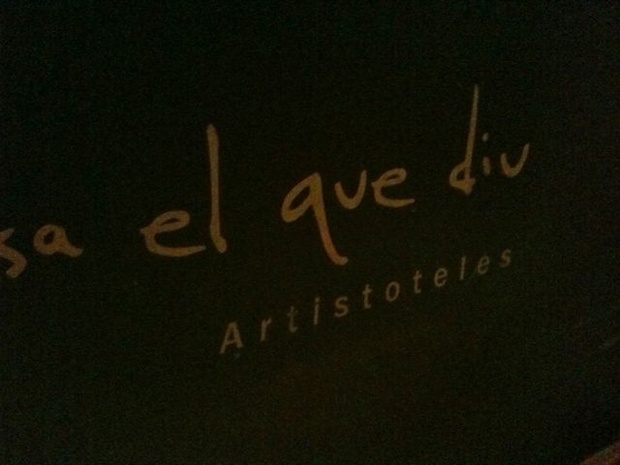
… Aschenpunzel
:mrgreen::biglove:
Lustig, das habe ich mich auch gefragt. Als Nordlicht habe ich bei dem Thema aber ohnehin einen blinden Fleck und weiß nicht wirklich, wo man in Deutschland überall Fasching/Karneval feiert.
Bin ja auch nicht gerade der Faschingsfreak. Es muss ja auch nicht gleich überall eine Karneval-Hochburg wie in Kölln, Mainz, etc. sein … bei uns verkleiden sich heute jedenfalls mit Freude die Kleinen und Faschings-Pfannkuchen gibt es auch überall.:party: Bei Euch nicht?
Außerdem … was lenkt Ihr hier schon wieder vom Thema ab? :mad:
Ich hab zwar mit Karneval nichts am Hut, aber hier in Braunschweig
waren am Sonntag über 100.000 Zuschauer beim Umzug. In den
Jahren zuvor lag die Beteiligung auch schon mal darüber.
Stimmt, wir lenken ab. Ich fand das Thema ja nur interessant, weil ich durch R::berts Post anfing, darüber nachzudenken, ob es in den ostdeutschen Bundesländern eigentlich auch eine Faschingstradition gibt. Wie gesagt: Ich habe davon keine Ahnung, in Hamburg ist Fasching außer bei den Kindern nicht wirklich in der Alltagskultur verankert. Fasching und Karneval sind ja eher in katholisch geprägten Gegenden beheimatet – auch das trifft ja bis aufs Eichsfeld eher nicht auf den Osten des Landes zu, oder? Ich lasse mich da aber gerne eines Besseren belehren. :-?
Ich transferieren die Frage mal schnell ins Kaffeehaus, dann können wir uns hier wieder den Fundstücken widmen.
Aha, da hat Microsoft also das neue Logo her. Jetzt verstehe ich auch, warum das so seltsam verzerrt aussieht: vermutlich haben sie einfach die Stützpunkte ein bißchen verschoben, damit sie keine Lizenzgebühren zahlen müssen.
:Schmunzel: So wird es sein. ;-)
Ich frage mich allerdings was mir die rote Apple-Prophezeiung sagen soll. Standortwechsel nach Japan oder Übernahme durch die Türkei?
Was macht jetzt diese Fischgeschichte schon wieder hier im Thread? :cry:
Oh, bin ich zu sehr vom Thema weg? Dachte nach den Schlübbies, dem Misereor-Schaukasten und Buntstift-Filmchen ist sowas hier möglich? Nicht? :-?
Wollte Euch doch auch die schöne Schreibschrift nicht vorenthalten. :roll:
Also hier geht es um typographische Fundstücke. Bizarre Vorlieben für anderer Leute Unterkleider sind bei MGI und Weltverbesserungsagitationsfilme im Café besser aufgehoben. :!:
Du hast das Bleistift-Filmchen und den Bastel- äh Schaukasten vergessen. ;-)
Na dann versuche ich mal in Zukunft mit einem schönen Typo-Juwel
Dein Gemüt wieder etwas auf zu muntern. :-)
Du hast das Bleistift-Filmchen und den Bastel- äh Schaukasten vergessen. ;-)
Ja, nee, kleinlich sind wir hier ja nun auch wieder nicht. ;-)
Fundstück aus einem spanischen Restaurant, in dem Zitate bedeutender Menschen die Wände zieren:
aber, aber, kathrin! du kennst ihn nicht? artistoteles, der künstlerische schmachtadonis von den spanischen dörfern, der mühlflügelante einwanderer mit dem blassgriechischen akzent! tsss.